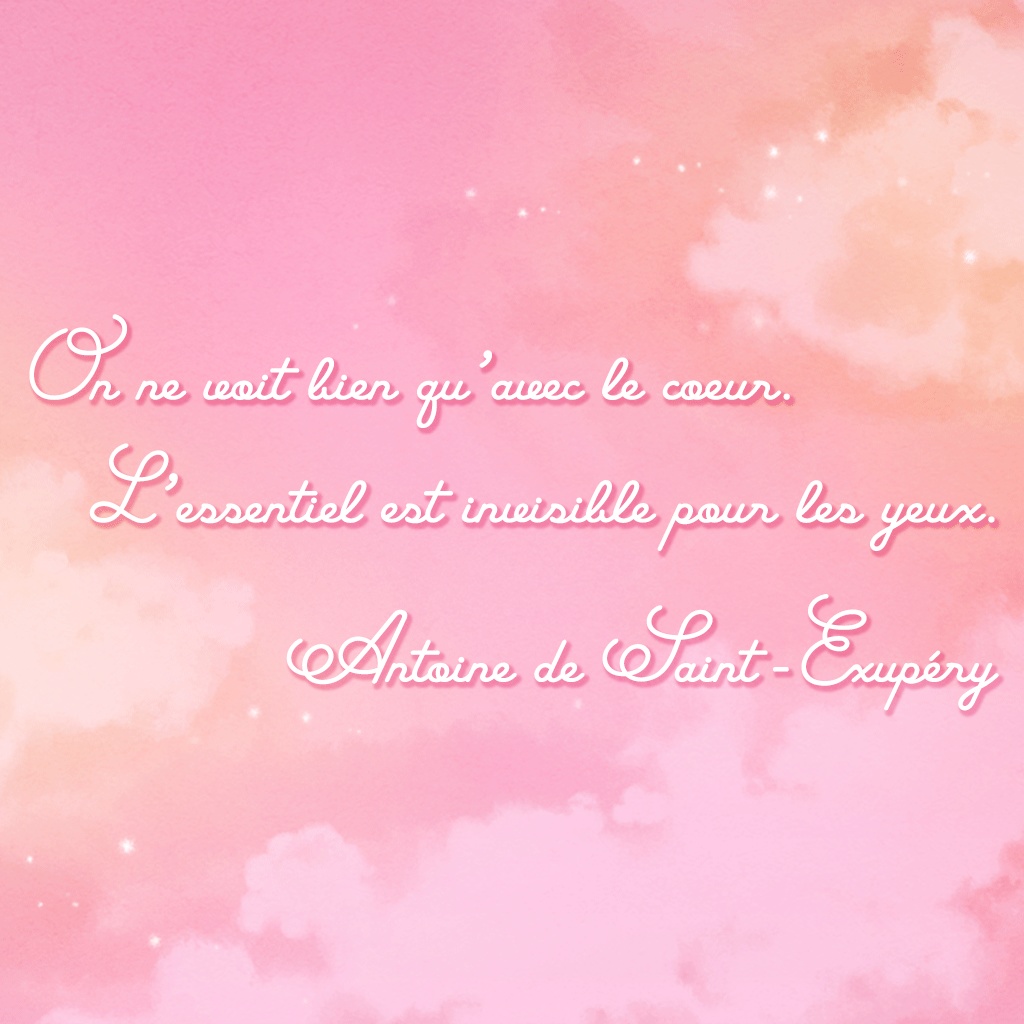
Mellow Melody(フリーフォント)
シンプルなスクリプト体のOpenTypeフォントです。 線に強弱のないなめらかなモノラインで親しみやすく、 イラストや写真に添えると やさしい雰囲気になるようなフォントを目指しました。 商用利用も可能なフリーフォントです。 どうぞご自由にお使いください。 こちらのフォントには異体字は入っていません。 普通に英数字や記号を打つことができます。 このフォントを気に入ってくださった方は SNSなどで紹介してもらえるととっても嬉しいです。 イメージ画像のPNGデータを添付しているので、 よろしければお使いください。 ★このフォントについて詳しくはこちら https://satsuyako.com/mellowmelody/ ★利用規約はこちら https://satsuyako.com/license-agreement/ 他にもフリーフォントを配布しているのでよかったら見てください! https://satsuyako.com/category/free-fonts/